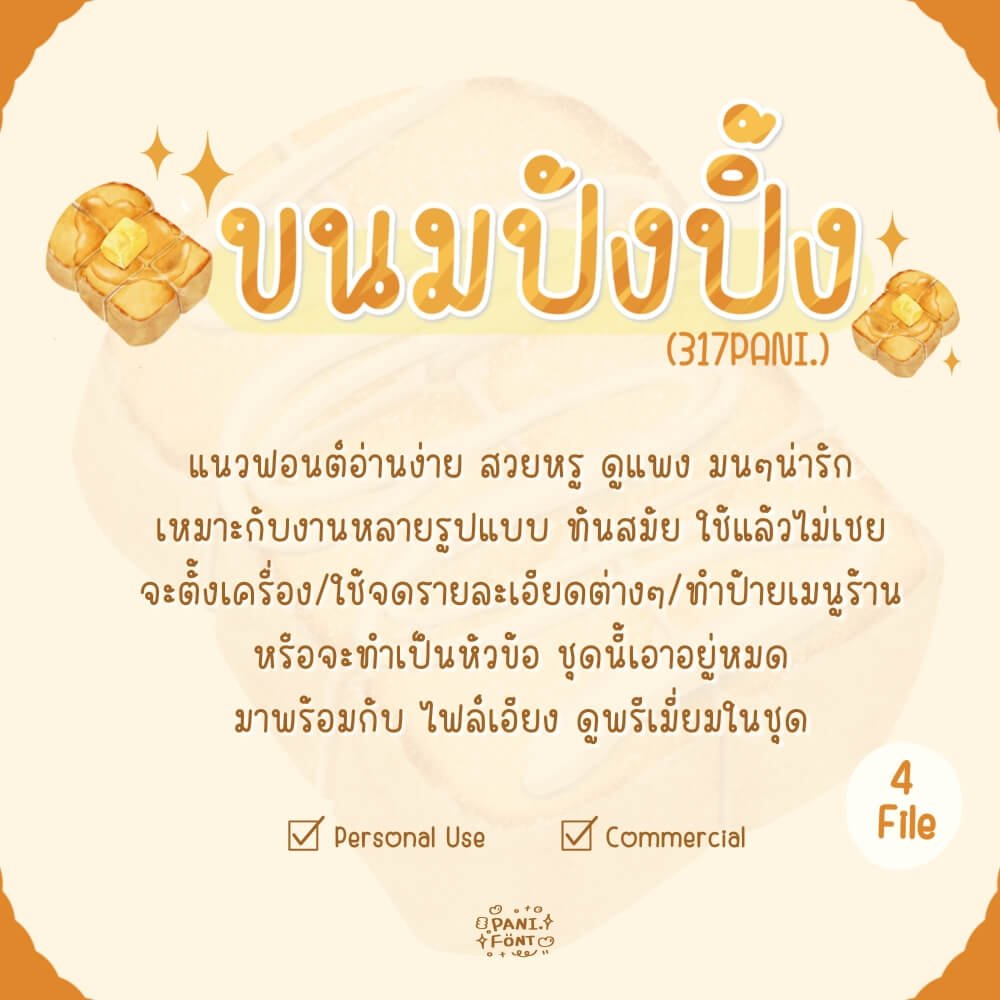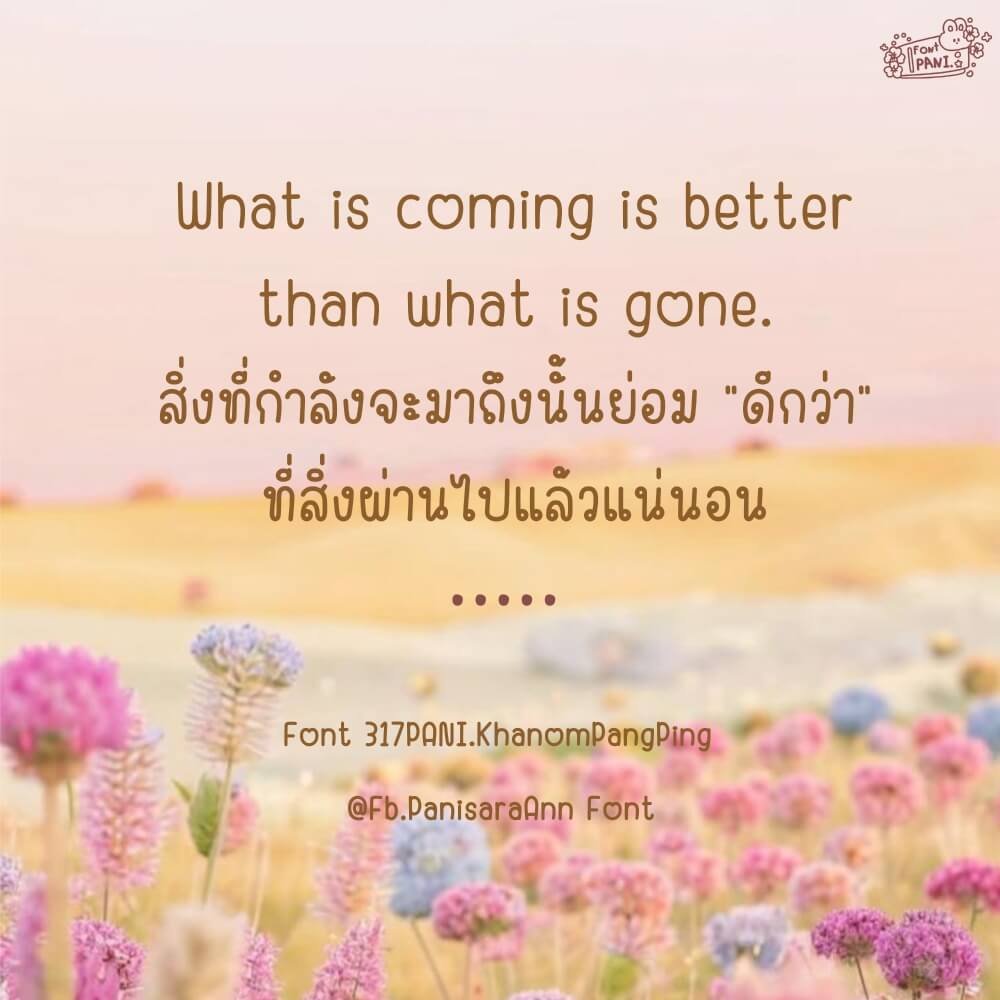
317PANI.ขนมปังปิ้ง (317PANIKhanomPangPing)
ฟอนต์ 317PANI.ขนมปังปิ้ง แจกฟรี!! ตัว Demo – ฟอนต์ตัวมนๆ น่ารัก เข้ากับยุคสมัย ชุดนี้แอนทำไฟล์เอียงให้ด้วยค่ะ เอียงนิดๆ กำลังสวย ไม่เยอะไป เป็นทางการแบบสมัยใหม่ ใครชอบแบบคุ้มค่า อ่านง่าย แนะนำค่ะ